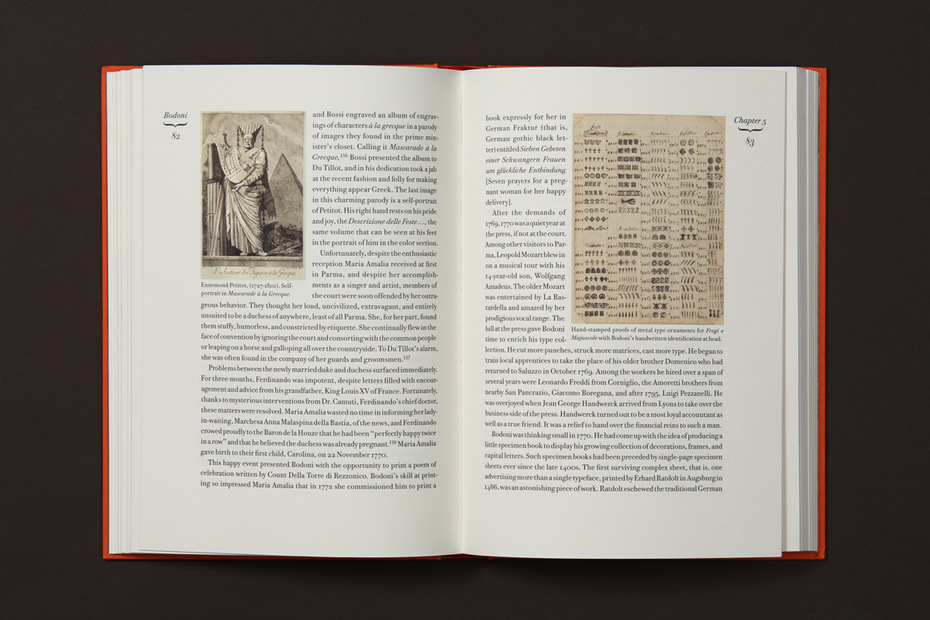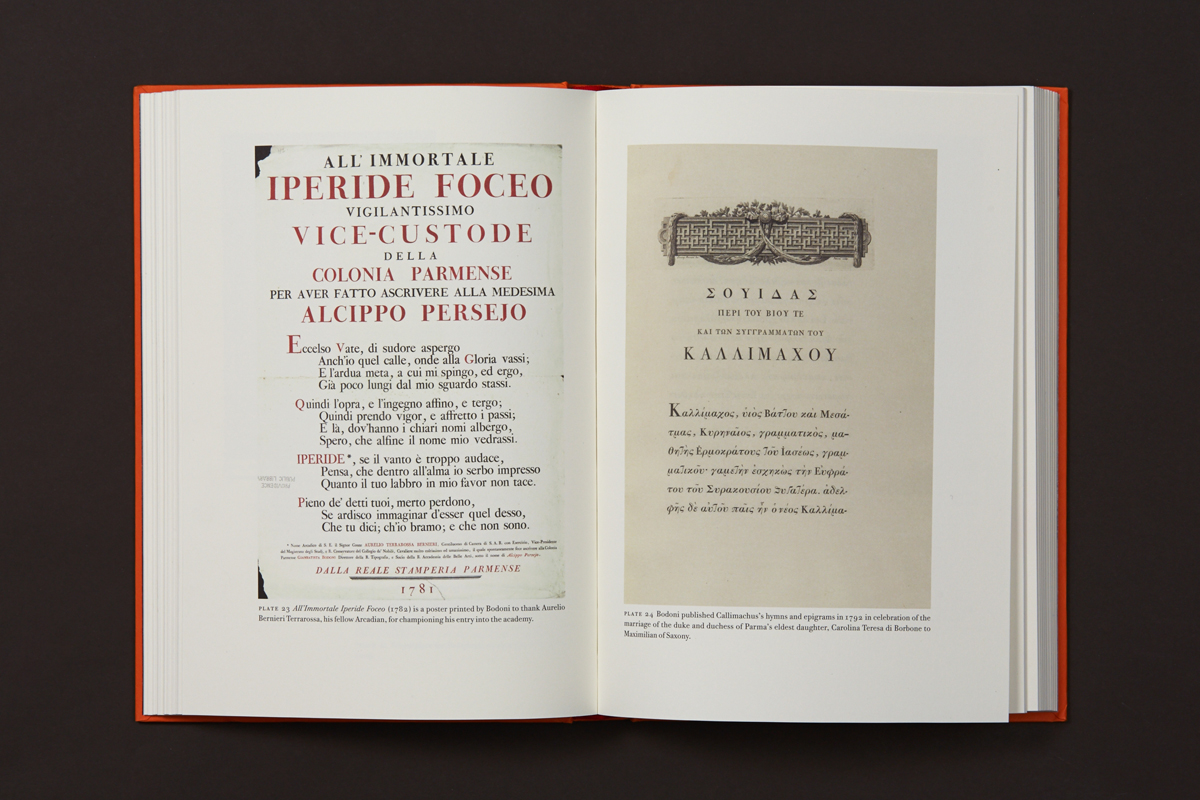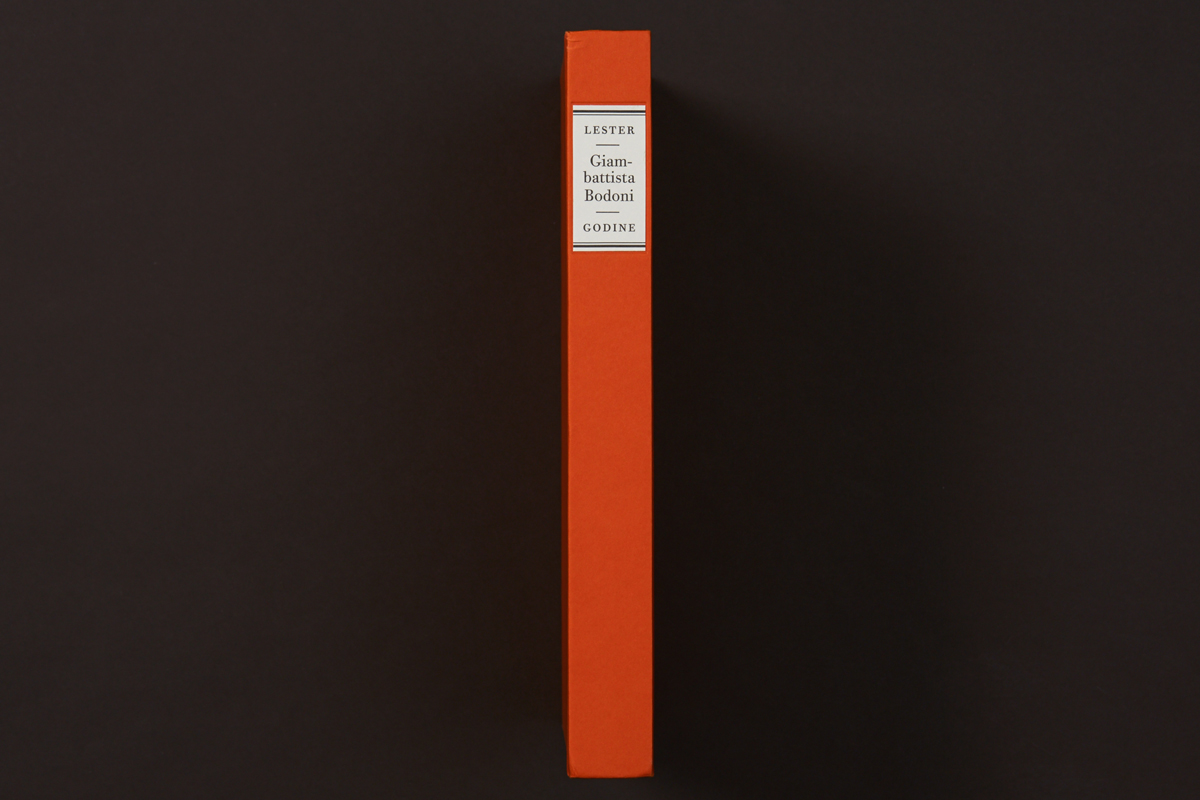
«Жизнь и эпоха Джамбаттисты Бодони» глазами Валери Лестер
ер­вой кни­гой по шриф­ту, ока­зав­шей­ся в мо­ей кол­лек­ции, бы­ла Anatomy of a Typeface Алек­сан­дра Ло­усо­на, по­свя­щён­ная ис­то­рии со­зда­ния клас­си­че­ских шриф­то­вых гар­ни­тур и вы­пу­щен­ная не­боль­шим аме­ри­кан­ским из­да­тель­ством David R. Godine. От­кры­тое в 1970 го­ду в Бо­сто­не, оно, по сло­вам осно­ва­те­ля Дэви­да Го­ди­на, спе­ци­а­ли­зи­ру­ет­ся «на кни­гах, ко­то­рые ни­кто не по­ку­па­ет». По­ми­мо ма­ло­ти­раж­ной ху­до­же­ствен­ной ли­те­ра­ту­ры, пе­ре­во­дов ино­стран­ных по­этов и пи­са­те­лей, книг для де­тей, из­да­тель­ство за го­ды су­ще­ство­ва­ния вы­пу­сти­ло не­сколь­ко де­сят­ков книг на те­му шриф­та, ти­по­гра­фи­ки и ис­кус­ства кни­ги, сре­ди ко­то­рых уже упо­мя­ну­тая Anatomy of a Typeface (1990), ре­принт An Essay on Typography Эри­ка Гил­ла (1993), пе­ре­из­да­ние A Tally of Types Ст­эн­ли Мо­ри­со­на (1999), по­след­нее из­да­ние глав­но­го тру­да Уол­те­ра Трей­си Letters of Credit (2003), а так­же Printer’s Devil — мо­но­гра­фия Сай­мо­на Локсли, по­свя­щён­ная аме­ри­кан­ско­му ти­по­гра­фу и ди­зай­не­ру шриф­та Фре­де­ри­ку Уор­ду (2013).
Са­мой но­вой в этом ря­ду ста­ла из­дан­ная чуть ме­нее по­лу­го­да на­зад био­гра­фия Джам­бат­ти­сты Бо­до­ни. Уди­ви­тель­но, но это пер­вая ко­гда-ли­бо вы­пу­щен­ная ан­гло­языч­ная био­гра­фия Бо­до­ни. Но осо­бен­но при­ме­ча­тель­на эта кни­га тем, что на­пи­сал её не ис­кус­ство­вед, не биб­лио­граф и не ди­зай­нер, а пи­са­тель­ни­ца, ни­ко­гда не за­ни­мав­ша­я­ся шриф­то­вой и ти­по­гра­фи­че­ской те­ма­ти­кой, — Ва­ле­ри Ле­стер (Valerie Browne Lester). Бо­лее то­го, и о ге­рое сво­ей бу­ду­щей кни­ги она уз­на­ла со­вер­шен­но слу­чай­но, во вре­мя зва­но­го ужи­на. Про­лог кни­ги, соб­ствен­но, со­дер­жит пе­ре­сказ этой увле­ка­тель­ной де­тек­тив­ной ис­то­рии. Хо­зя­ин ве­че­ра, биб­лио­фил и кол­лек­ци­о­нер, со­об­щил го­стям, что кни­га, яв­ляв­ша­я­ся вен­цом его кол­лек­ции, ока­за­лась кра­де­ной и что её пред­сто­ит вер­нуть за­кон­но­му вла­дель­цу. Этой кни­гой был глав­ный труд жиз­ни Бо­до­ни — Manuale Tipografico, вы­пу­щен­ный в 1818 го­ду. Пи­са­тель­ни­ца, ис­кав­шая в тот мо­мент те­му для сво­ей но­вой кни­ги, сра­зу по­ня­ла: вот оно. Спер­ва её за­ин­те­ре­со­вал факт кра­жи, и она на­ча­ла изу­чать об­сто­я­тель­ства про­изо­шед­ше­го, вы­яс­нив, что за по­хи­ще­ни­ем цен­но­го эк­зем­пля­ра (ны­не сто­и­мость кни­ги ко­леб­лет­ся в диа­па­зо­не от 35 до 47 тыс. дол­ла­ров) сто­ит жен­щи­на, имев­шая не­огра­ни­чен­ный до­ступ в биб­лио­те­ку Уни­вер­си­те­та Те­ха­са в Ости­не, в том чис­ле бла­го­да­ря ро­ман­ти­че­ской свя­зи с уни­вер­си­тет­ским биб­лио­те­ка­рем.
В про­цес­се соб­ствен­но­го пи­са­тель­ско­го рас­сле­до­ва­ния Ва­ле­ри Ле­стер всё боль­ше и боль­ше про­яв­ля­ла ин­те­рес к лич­но­сти Бо­до­ни и, с удив­ле­ни­ем узнав, что, по­ми­мо не­боль­шо­го, на­пи­сан­но­го в 1913 го­ду био­гра­фи­че­ско­го эс­се, о нём не бы­ло пуб­ли­ка­ций на ан­глий­ском, ре­ши­ла «оста­вить рас­сле­до­ва­ни­е кра­жи, при­че­сать уже под­за­бы­тый ита­льян­ский и на­пра­вить­ся в Ита­лию во­сем­на­дца­то­го сто­ле­тия, во вре­ме­на Джам­бат­ти­сты Бо­до­ни». Ис­то­рия, ко­то­рую пи­шет Ле­стер, со­всем не мо­но­тон­на и изо­би­лу­ет де­та­ля­ми, сце­на­ми жиз­ни и бы­та. В гла­ве о дет­стве Бо­до­ни, на­при­мер, она пе­ре­чис­ля­ет ха­рак­тер­ные блю­да сто­лов зна­ти Пье­мон­та то­го вре­ме­ни, вклю­чав­шие по­ми­мо про­че­го зай­ча­ти­ну, яг­ня­ти­ну, угрей и да­же фри­кас­е из ля­гу­шек, а так­же при­во­дит опи­са­ние про­цес­са за­вар­ки ко­фе по мо­де то­го вре­ме­ни (пол­то­ры ун­ции мо­ло­то­го ко­фе на пин­ту ки­пят­ка). А в гла­ве, по­свящён­ной пре­бы­ва­нию мо­ло­до­го Бо­до­ни в Ри­ме, где упо­ми­на­ет­ся биб­лио­те­ка кар­ди­на­ла Пь­ет­ро От­то­бо­ни, о по­след­нем она со­об­ща­ет сле­ду­ю­щее: «Это был кар­ди­нал, це­ли­ком по­свя­тив­ший се­бя му­зы­ке, ис­кус­ству, ар­хи­тек­ту­ре и сек­су­аль­ным от­но­ше­ни­ям. По­го­ва­ри­ва­ли, что в его по­ко­ях ви­се­ли кар­ти­ны, изоб­ра­жав­шие его лю­бов­ниц в об­ра­зах свя­тых, а сам он яв­лял­ся от­цом то ли 60, то ли 70 де­тей».
Сра­зу по­сле оглав­ле­ния ав­тор, как в пье­се, пред­став­ля­ет дей­ству­ю­щих
лиц сво­е­го про­из­ве­де­ния в по­ряд­ке упо­ми­на­ния их в кни­ге. Сре­ди них, по­ми­мо глав­но­го ге­роя: его се­мья, в ко­то­рой дед Джан­до­ме­ни­ко Бо­до­ни, отец Фран­че­ско Бо­до­ни, бра­тья До­ме­ни­ко и Джу­зеп­пе ра­бо­та­ли пе­чат­ни­ка­ми или бы­ли свя­за­ны с ти­по­граф­ским де­лом; рим­ские и парм­ские свя­щен­ни­ки; ита­льян­ская и фран­цуз­ская знать; лич­ные по­кро­ви­те­ли и дру­зья Бо­до­ни; его су­пру­га Мар­га­ри­та; На­по­ле­он Бо­на­парт с Жо­зе­фи­ной. По­вест­во­ва­ние по­де­ле­но на 18 глав, свя­зан­ных с основ­ны­ми пе­ри­о­да­ми ли­бо глав­ны­ми со­бы­ти­я­ми жиз­ни Бо­до­ни. Рас­сказ о его ра­бо­те и твор­че­стве пе­ре­ме­жа­ет­ся с со­бы­ти­я­ми из лич­ной жиз­ни, об­сто­я­тель­ства­ми его от­но­ше­ний с дво­ром Пар­мы, зна­ком­ства с су­пру­гой, а так­же опи­са­ни­ем не­ду­гов, ко­то­рые пре­сле­до­ва­ли его до кон­ца жиз­ни. Кни­га снаб­же­на при­ло­же­ни­я­ми, ав­тор­ски­ми при­ме­ча­ни­я­ми, имен­ным ука­за­те­лем и по­дроб­ным спис­ком ис­поль­зо­ван­ных изоб­ра­же­ний и ре­про­дук­ций.
Во вре­ме­на Бо­до­ни ма­стер-ти­по­граф был боль­ше чем про­сто ма­ке­ти­ров­щи­ком и на­бор­щи­ком: ему не­об­хо­ди­мо бы­ло уметь на­ри­со­вать бук­ву, на­ре­зать пу­ан­сон, вы­бить им мат­ри­цу, от­лить в ней ли­те­ру, раз­ме­стить ли­те­ру в на­бо­ре и от­тис­нуть на бу­ма­ге. Ма­стер­ство Бо­до­ни про­сти­ра­лось даль­ше и это­го ши­ро­ко­го на­бо­ра на­вы­ков. Ещё бу­ду­чи со­всем мо­ло­дым, ра­бо­тая в Ри­ме в ти­по­гра­фии Ва­ти­ка­на, он за­ни­мал­ся сор­ти­ров­кой и ка­та­ло­ги­за­ци­ей пу­ан­со­нов эк­зо­ти­че­ских ал­фа­ви­тов, а так­же осво­ил на­ча­ла араб­ско­го и древ­не­еврей­ско­го язы­ков. Мно­го­языч­ный на­бор в то вре­мя раз­ви­вал­ся как ни­ко­гда преж­де, из­да­ния, по­сту­пав­шие из Азии и с Ближ­не­го Вос­то­ка, тре­бо­ва­ли пе­ре­пе­чат­ки и рас­про­стра­не­ния сре­ди учё­ных Ев­ро­пы.
На про­тя­же­нии всей сво­ей даль­ней­шей жиз­ни он ре­зал пу­ан­со­ны букв раз­лич­ных ал­фа­ви­тов и да­же хо­тел вы­пу­стить из­да­ние, по­свя­щён­ное ис­клю­чи­тель­но эк­зо­ти­че­ским язы­кам, од­на­ко в по­след­ний мо­мент уже го­то­вые от­ли­тые ли­те­ры для кни­ги бы­ли укра­де­ны охот­ни­ка­ми за цвет­ны­ми ме­тал­ла­ми, ре­шив­ши­ми, что бук­вы сде­ла­ны из се­ре­бра. По­сле не­дол­гих по­ис­ков во­ров уда­лось най­ти, од­на­ко боль­шая часть ли­тер к то­му мо­мен­ту уже бы­ла рас­плав­ле­на в ско­во­род­ках на кух­не же­ной од­но­го из со­участ­ни­ков. По­зд­нее не­ко­то­рые из этих на­бор­ных ал­фа­ви­тов, как и дру­гие, вклю­чая рус­ский гра­ждан­ский, ста­нут не­отъ­ем­ле­мой ча­стью Manuale Tipografico, за­вер­шен­но­й вдо­вой Бо­до­ни и вы­пу­щен­но­й уже по­сле его смер­ти. Ско­рость ра­бо­ты Бо­до­ни так­же по­тря­са­ла. У опыт­но­го рез­чи­ка ухо­ди­ло до пя­ти ча­сов на один пу­ан­сон сред­не­го раз­ме­ра, в то вре­мя как Бо­до­ни, по сло­вам од­но­го из го­стей ти­по­гра­фии, был спо­со­бен сде­лать но­вый, от­но­си­тель­но не­слож­ный шрифт од­но­го кегля за два-три дня. Во вре­мя ин­вен­та­ри­за­ции его кол­лек­ции в 1840 го­ду бы­ло на­счи­та­но 25 735 пу­ан­со­нов и 50 994 мат­ри­цы — не­мыс­ли­мое по тем вре­ме­нам ко­ли­че­ство.
Из кни­ги мож­но узнать о том, что Бо­до­ни ещё при жиз­ни про­сла­вил­ся в пер­вую оче­редь как из­да­тель и пе­чат­ник; что спер­ва он бо­го­тво­рил Бас­кер­вил­ля и да­же от­пра­вил­ся в пу­те­ше­ствие к не­му в Ан­глию, пре­рван­ное из-за ма­ля­рии и так ни­ко­гда и не ­со­сто­яв­ше­е­ся, а поз­же по­но­сил его за из­бы­точ­ную де­ко­ра­тив­ность на­бор­ных ти­ту­лов; о на­сто­я­щей вой­не слу­хов и ре­пу­та­ций меж­ду Бо­до­ни и па­риж­ским се­мей­ством пе­чат­ни­ков Ди­до, со­про­во­ждав­шей­ся сле­ду­ю­щи­ми за­яв­ле­ни­я­ми в ад­рес ита­льян­ца, сде­лан­ны­ми в раз­ные го­ды Пье­ром Ди­до: «Ве­ли­чие букв, со­здан­ных им, де­ла­ет ошиб­ки в его кни­гах ещё бо­лее за­мет­ны­ми» и Фир­ме­ном Ди­до: «Как ли­те­ра­тор я про­кли­наю его из­да­ния, но как ти­по­граф я вос­хи­ща­юсь ими»; о пись­ме Бен­джа­ми­на Фран­кли­на, в ко­то­ром он от­ме­чал ви­ден­ны­е им кни­ги Бо­до­ни и его на­бор­ные шриф­ты, мяг­ко пе­ре­хо­дя к по­дроб­ным за­ме­ча­ни­ям от­но­си­тель­но фор­мы зна­ков и но­та­ци­ям. По­ми­мо соб­ствен­но био­гра­фии Бо­до­ни, из­да­ние вклю­ча­ет че­ты­ре при­ло­же­ния-эс­се: Ст­э­на Не­ль­со­на о тех­но­ло­гии на­рез­ки пу­ан­со­нов, о штам­пов­ке мат­риц и от­лив­ке ли­тер, Фре­да и Бар­ба­ры Волт­мер о пе­ча­ти на руч­ном пе­чат­ном стан­ке и ис­то­ри­ка шриф­та Джейм­са Мо­сли о про­пав­шем «три­ест­ском ли­сте» из пер­во­го, не столь объ­ём­но­го и слож­но­го по срав­не­нию с по­смерт­ным, из­да­ния Manuale Tipografico (1788).
Ва­ле­ри Ле­стер рас­ска­зы­ва­ет о кни­ге и ис­точ­ни­ках вдох­но­ве­ния.
Кни­га Ва­ле­ри Ле­стер оформ­ле­на из­вест­ным аме­ри­кан­ским книж­ным ди­зай­не­ром Джер­ри Кел­ли, на­бра­на уме­рен­но кон­траст­ной вер­си­ей мел­ко­ке­гель­но­го Bodoni от ITC, в то вре­мя как за­го­ло­воч­ный на­бор вы­пол­нен вер­си­ей от Bauer. В из­да­нии мож­но уви­деть боль­шие по­лос­ные и вну­три­тек­сто­вые ре­про­дук­ции ти­ту­лов книг Бо­до­ни, мат­риц и пу­ан­со­нов, пор­тре­ты со­вре­мен­ни­ков, зна­ко­мых и дру­зей ге­роя. На­вер­ня­ка нам хо­те­лось бы уви­деть ещё боль­ше при­ме­ров книг и шриф­тов Бо­до­ни, но ис­кус­ство­вед­че­ский и ти­по­гра­фи­че­ский ана­лиз его на­сле­дия не яв­ля­лись глав­ны­ми це­ля­ми это­го из­да­ния. За­ин­те­ре­со­вав­ши­е­ся чи­та­те­ли смо­гут най­ти не­ко­то­рые из его книг в Се­ти в элек­трон­ных биб­лио­те­ках, а об­раз­цы шриф­тов — в ре­прин­тах Manuale Tipografico, по­след­ний из ко­то­рых, с пе­ре­ве­дён­ны­ми на ан­глий­ский пре­ди­сло­ви­я­ми Бо­до­ни и его вдо­вы, был вы­пу­щен не­мец­ким из­да­тель­ством Taschen в 2010 го­ду.
По­сле про­чте­ния этой био­гра­фии Бо­до­ни стал осо­бен­но ин­те­ре­сен мне как че­ло­век, предвос­хи­тив­ший эпо­ху «Юни­ко­да» ещё в XVIII ве­ке. Кни­ги, вы­пус­кав­ши­е­ся им в ти­по­гра­фии гер­цо­га Пар­мы и в сво­ей част­ной ти­по­гра­фии, на­би­ра­лись ла­ты­нью, гре­че­ским, ита­льян­ским, фран­цуз­ским, ан­глий­ским и не­мец­ким, при этом сим­во­лы этих и дру­гих, бо­лее ред­ких и эк­зо­ти­че­ских язы­ков со­зда­ва­лись им са­мим. В 1806 го­ду по за­ка­зу па­пы Пия VII он из­дал Oratio Dominica, кни­гу, со­дер­жав­шую текст мо­лит­вы «От­че наш» на 155 язы­ках, спе­ци­аль­но для ко­то­рой бы­ло со­зда­но 97 эк­зо­ти­че­ских ал­фа­ви­тов, вклю­чая огра­ни­чен­ный на­бор ки­тай­ских иеро­гли­фов. Джам­бат­ти­ста Бо­до­ни, а по­сле его смер­ти и его су­пру­га, сво­им ре­ме­слом и усер­ди­ем слу­жи­л на бла­го и для раз­ви­тия ци­ви­ли­за­ции, ко­то­рую се­го­дня мы на­зы­ва­ем ев­ро­пей­ской. «Я бы­ла осве­дом­ле­на о тя­же­сти та­ко­го на­чи­на­ния, од­на­ко со­бра­ла все свои си­лы; моя лю­бовь к Не­му и во имя Не­го под­дер­жи­ва­ла ме­ня. Я от­важ­но всту­пи­ла в это пред­при­я­тие, да­бы Ита­лия и Ев­ро­па не бы­ли ли­ше­ны столь вы­да­ю­ще­го­ся па­мят­ни­ка ти­по­гра­фи­че­ско­го ис­кус­ства», — ­на­пи­шет о за­вер­ше­нии ра­бо­ты над Manuale Tipografico в его пре­ди­сло­вии вдо­ва Бо­до­ни Мар­га­ри­та Даль’Альо.
Некоторые современные интерпретации шрифтов Бодони:
1. Berthold Bodoni Old Face (1986), Гюнтер Герард Ланге (Günter Gerard Lange)
2. WTC Our Bodoni (1989), Массимо Виньелли, Том Карнезе (Massimo Vignelli, Tom Carnase)
3. Linotype Gianotten (1990), Антонио Пасе (Antonio Pace)
4. DTP New Bodoni DT (1992), Малкольм Вуден (Malcolm Wooden)
5. FF Bodoni Classic (1994–1995), Герт Вишер (Gert Wiescher)
6. ITC Bodoni (1994), Самнер Стоун, Джим Паркинсон, Холли Голдсмит, Дженис Фишман (Sumner Stone, Jim Parkinson, Holly Goldsmith, Janice Fishman)
7. Omnibus Bodoni Classico (1995), Франко Люин (Franco Luin)
8. ITC Bodoni 72 (кириллическая версия, 2000), Дмитрий Кирсанов
9. Emigre Filosofia (1996, 2012 — кириллическая версия), Зузана Личко (Zuzana Ličko), Гаянэ Багдасарян
10. Caponi (2014), Мигель Райес, Кристиан Шварц, Пол Барнс (Miguel Reyes, Christian Schwarz, Paul Barns)
11. Parmigiano (2015), Ри­кар­до Оло­ку (Riccardo Olocco), Джо­на­тан Пье­ри­ни (Jonathan Pierini), Илья Ру­дер­ман и Ири­на Смир­но­ва (ки­рил­ли­ца), Ирен Вла­ку (гре­че­ский)